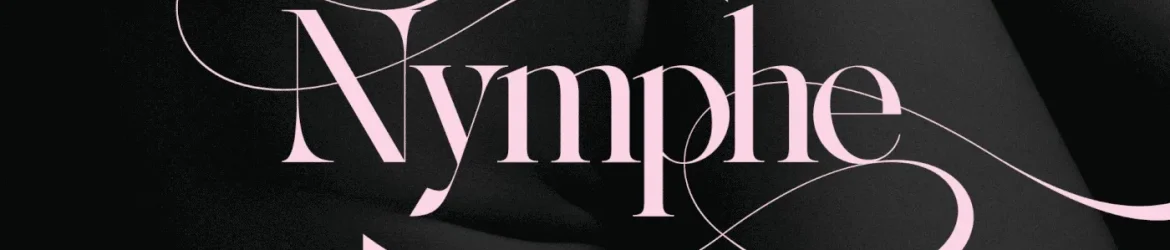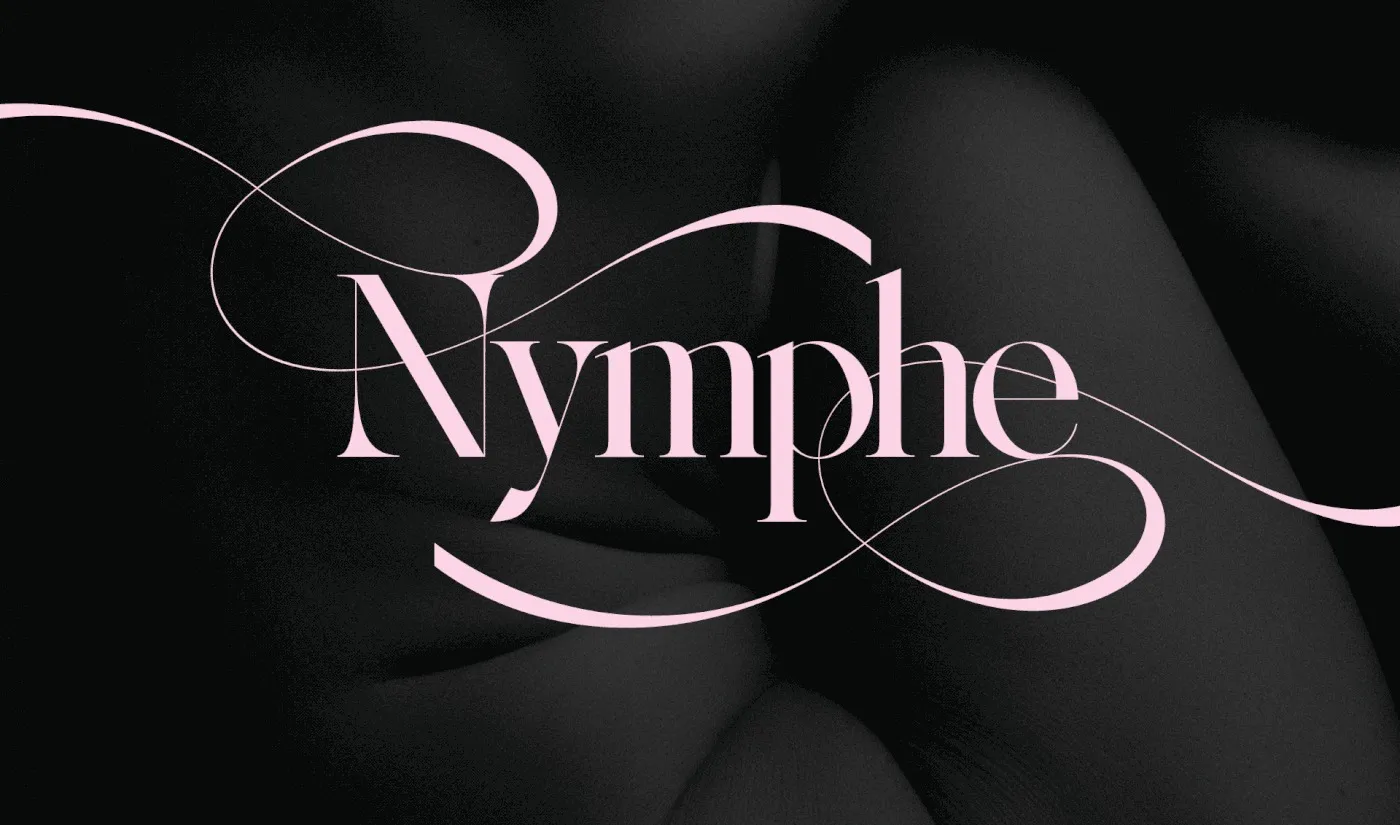
Nympha Font Family
A Nympha Font Family é uma elegante família de serif que oferece tanto beleza quanto contemporaneidade para seus projetos tipográficos. Criada pela OnRepeat Studio, essa fonte tem 10 tipos distintos, incluindo ligaturas e alternativas de caracteres, além de suporte a múltiplas línguas. Suas linhas fortes contrastam com detalhes refinados, enquanto suas formas elegantes e curvas voluptuosas criam um impacto poderoso e atraente. Esta família é perfeita para aqueles que buscam uma combinação de glamour e estética contemporânea em seus projetos. Não importa o projeto – esta família de fontes trará um toque elegante ao seu design, seja em letras grandes ou em detalhes menores.